告别海量搜索,一个文章帮你集齐所需的中文字体库
找中文字体是很多人做设计时的第一道坎。网上搜汉字字体字库,结果分散在各个论坛、网盘和博客里,下载下来还要担心格式兼容和授权问题。有些网站号称免费,实际只提供个人使用,商用需要额外付费;有些字体文件本身就不完整,安装后缺字或者显示异常。这篇文章整理了五个实用的中文字体资源平台,覆盖筛选、下载、预览和管理等多个环节,帮你把找字体这件事变得更简单一些。
字由目前维护的字体资源超过一万款,免费商用部分有3000 余款。它的核心能力不是单纯提供下载链接,而是把筛选、预览、收藏和调用整合在一个流程里,更像一个系统级的汉字字体字库管理的综合性平台。
面对上万款字体,最头疼的是不知道从何下手。字由的汉字字体字库筛选维度做得比较细,除了常规的宋体、黑体、楷体、行书等分类标签,还支持按使用场景过滤。比如你要做品牌VI,需要找一套识别度高、字重齐全的中文字体,直接勾选商务或者品牌分类,结果列表就会缩小到符合条件的范围。配合字重筛选,你可以进一步锁定具备细体、常规、粗体、特粗等多个版本的字体家族,这对做VI手册时统一不同层级的排版很有帮助。
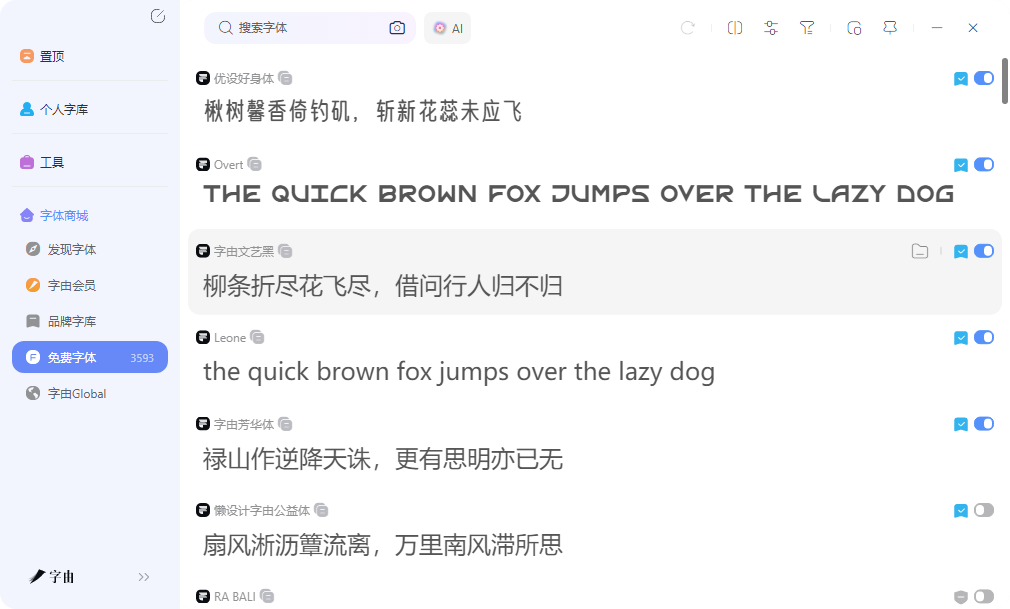
免费商用标签是字由筛选体系里的关键一环。每款字体都标注了授权信息,勾选免费商用后,结果列表里只会显示允许商用的选项。对于接商业项目的设计师来说,这个标签省去了逐个确认授权的麻烦,也降低了侵权风险。字由的免费商用汉字字体字库里有不少实用性很高的选择,比如优设标题黑,笔画粗重有设计感,适合海报主标题;仓耳渔阳体风格现代简洁,做品牌VI的基础字形比较稳妥;鸿雷板书简体带有手写温度,文创类项目用起来很合适。这几款字体都标注了免费商用标签,激活后可以直接用于商业项目。
预览功能也做得比较实用。在字由客户端或者网页版里,直接点击任意一款字体,在预览框里输入自己的文案,就能实时看到效果。这个细节在挑选标题字时特别有用,因为同样的字体显示不同文字,视觉感受可能完全不同。看到合适的字体,一键收藏到个人分组,后续需要时直接从收藏夹调用,不用重新搜索。
2、喵闪字库
这是一个专注于中文字体的资源平台,首页把字体按黑体、宋体、圆体、楷体、书法、手写、卡通等类型做了分类。顶部有免费商用筛选按钮,点击后结果列表会只显示允许免费商用的字体,这个设计对需要商用素材的设计师来说很直接,不用逐个查看授权说明。每款字体都支持在线预览,输入文字后可以直接看到效果,确认合适后再下载,避免下载后发现风格不符再删除的麻烦。
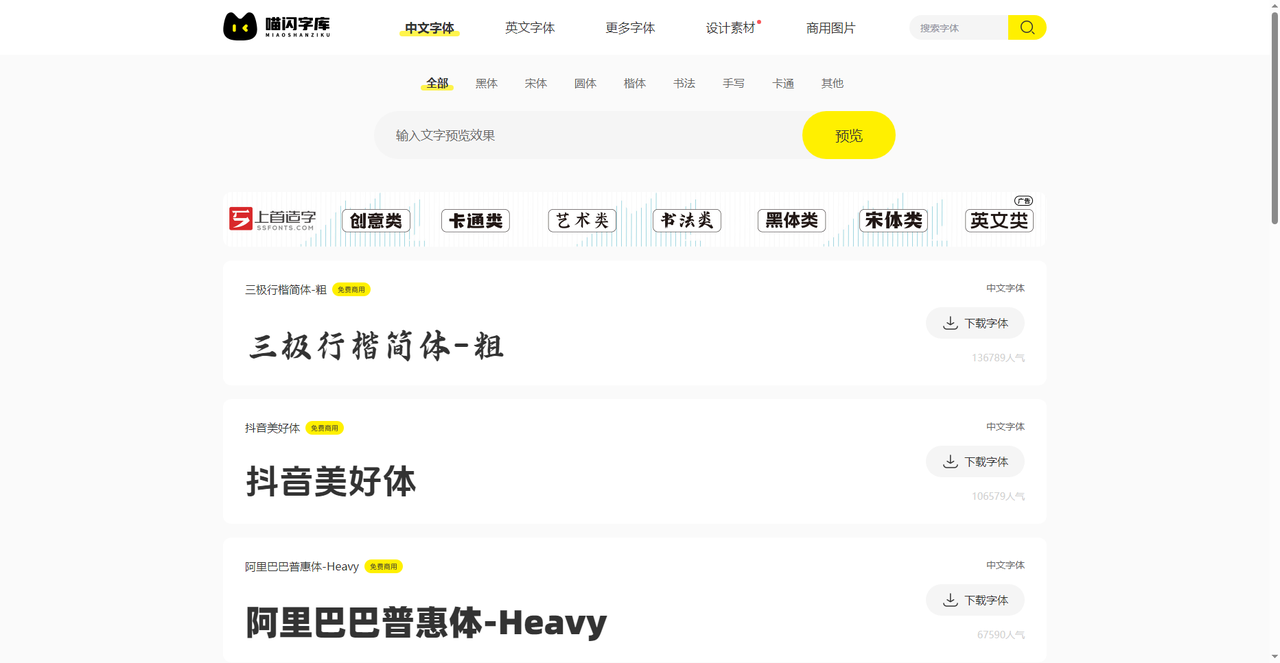
3、模板王
模板王的中文字体下载板块收录了超过4000款字体,左侧导航按宋体、楷体、行书、隶书、草书等书法体系做了详细分类。这种分类方式对需要特定书法风格的用户很友好,比如要找一款隶书做传统文化海报,直接点进隶书分类就能看到全部候选,不需要在海量字体里翻找。每款字体都配有预览图和下载按钮,部分字体标注了商用授权信息,下载前可以一目了然。需要注意的是,下载前最好确认授权范围,部分字体可能仅限个人使用,商用需要额外申请授权。模板王除了字体下载,还提供了不少设计模板和素材,虽然本文主要关注字体部分,但这种资源整合对做完整项目的人来说比较方便,可以在同一个平台找到配套资源。对于喜欢书法风格字体的用户来说,模板王的分类深度是一个不错的参考来源。
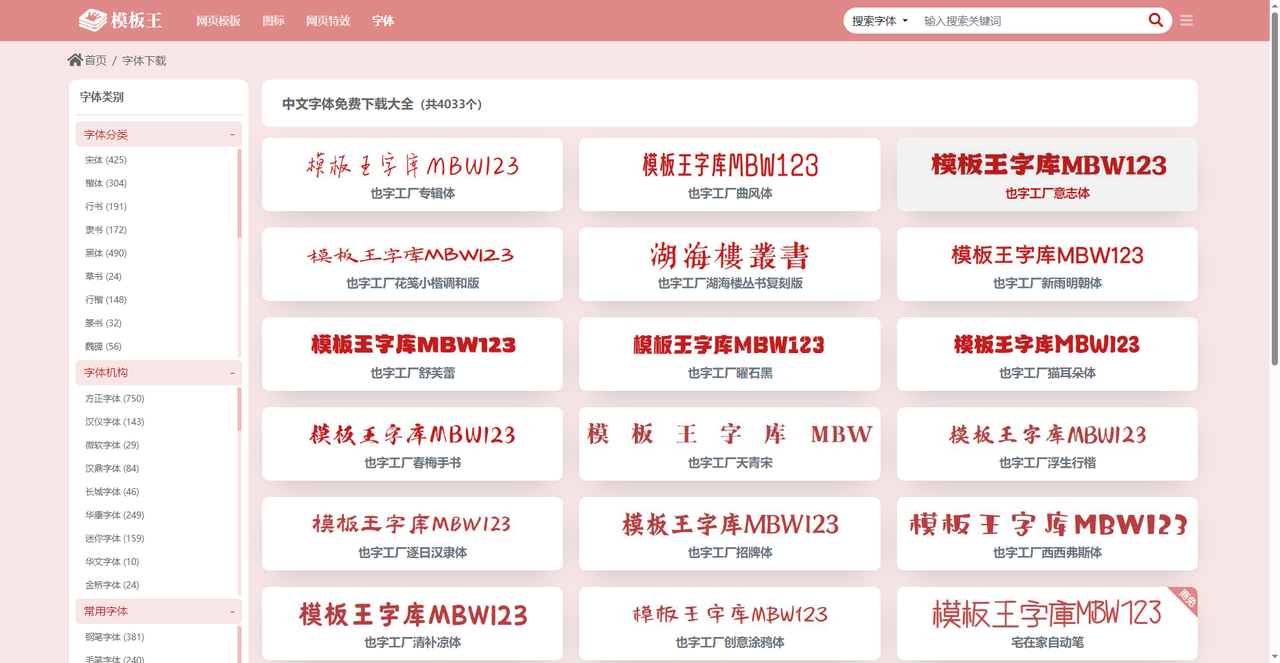
4、站长字体
站长字体是一个综合性的汉字字体字库平台,目前收录的免费商用字体超过2600款。站长字体的资源覆盖面比较广,从常规印刷体到创意艺术字都有涉及,适合需要一站式浏览多厂商资源的用户。对于不确定某款字体名称的场景,AI识别功能可以省去很多猜测的时间。站长字体的更新频率比较可观,经常会有新的厂商字体加入,关注一段时间可以持续发现新资源。对于需要保持字体库新鲜度的设计师来说,这种持续更新的机制比较实用。
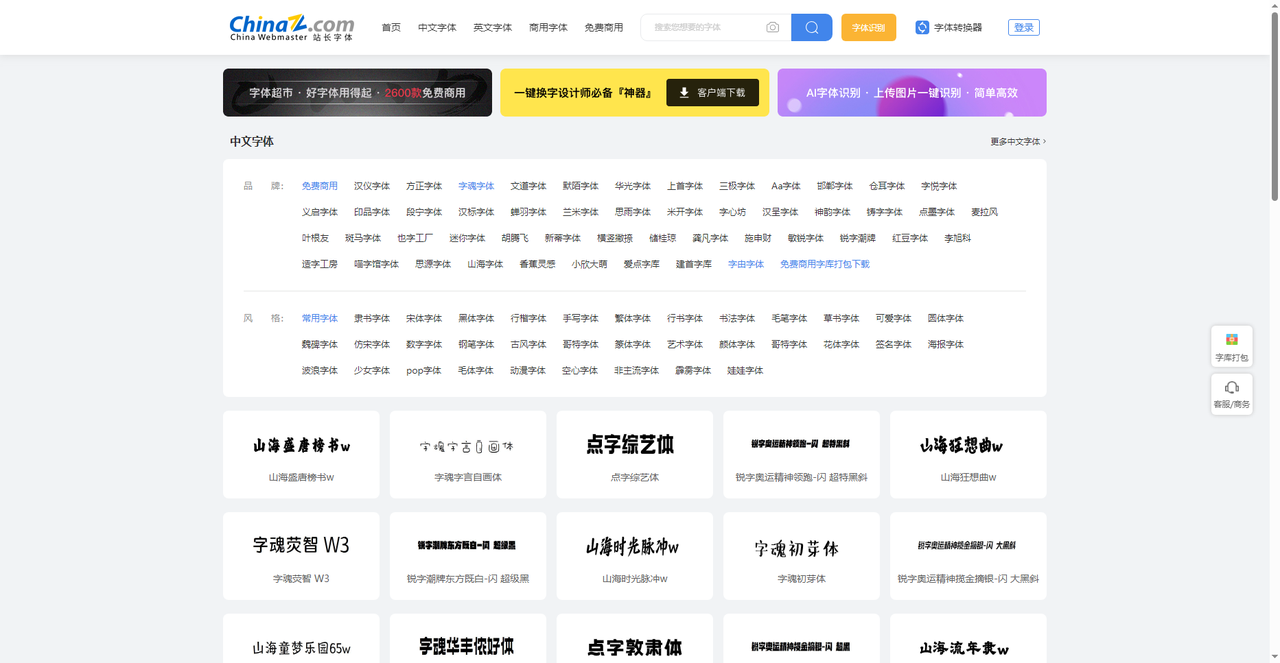
5、字体天下
字体天下是一个大型的汉字字体字库,目前收录的字体数量超过10000款。首页按字母顺序、风格类型和字体厂商做了多维度索引,你可以通过拼音首字母快速定位到特定字体,也可以按风格标签浏览,比如想找一款复古风格的海报字体,直接点进对应标签就能看到相关集合。平台支持在线预览功能,输入文字后实时查看效果,避免下载后发现不合适。
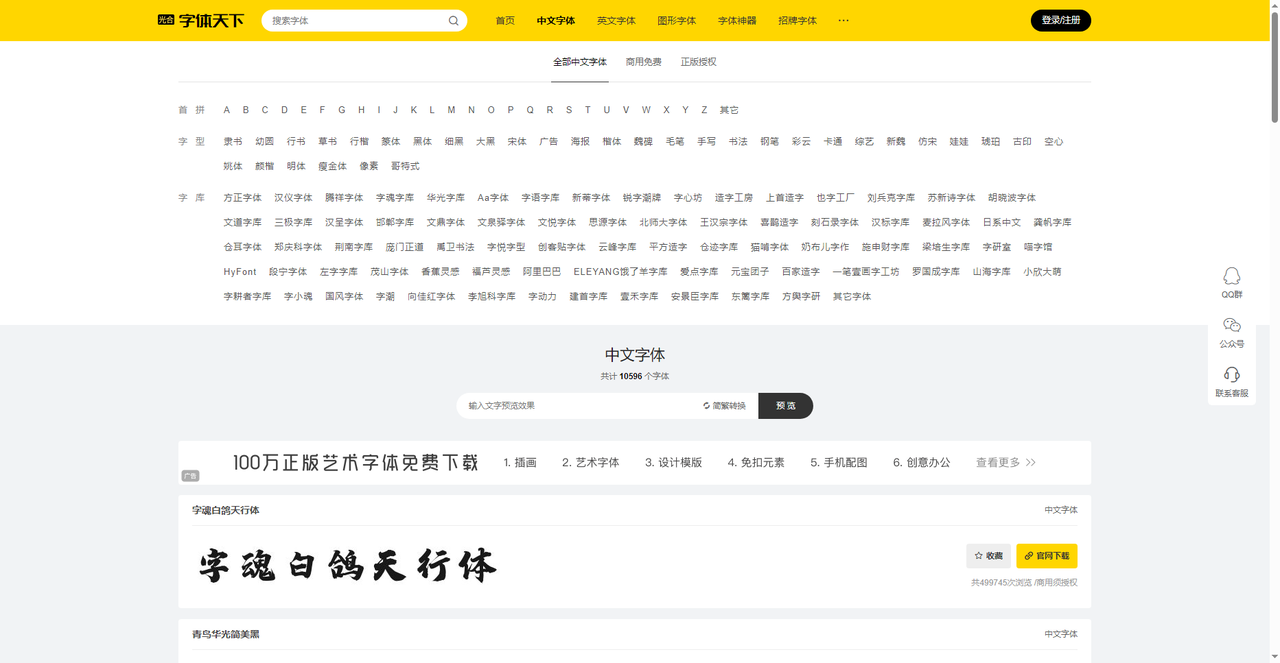
如果你需要系统性地管理和筛选汉字字体字库,字由的跨设备同步、多维度筛选和一键收藏功能可以省去很多重复操作,免费商用标签也能降低版权风险。其余四款工具的共同点是均聚焦于字体资源的展示与单一下载,无法提供系统级的字体管理、跨软件即时调用和云同步功能。